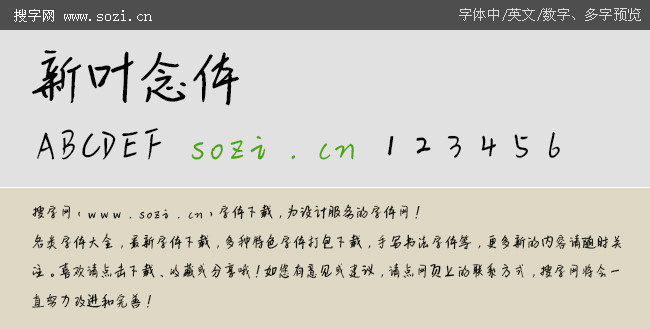
新葉念體
搜字網(wǎng)給大家提供一款新葉念體中文手寫書法字體下載,是一款新葉傳媒開發(fā)的非常漂亮的硬筆手寫體字體,新葉念體采用GB2312編碼,約6900字,念是惦記,是想念,是思念,是牽掛。手寫字有著強(qiáng)烈的人文氣息,紙短情長(zhǎng),見(jiàn)字如面,您可以免費(fèi)商用。